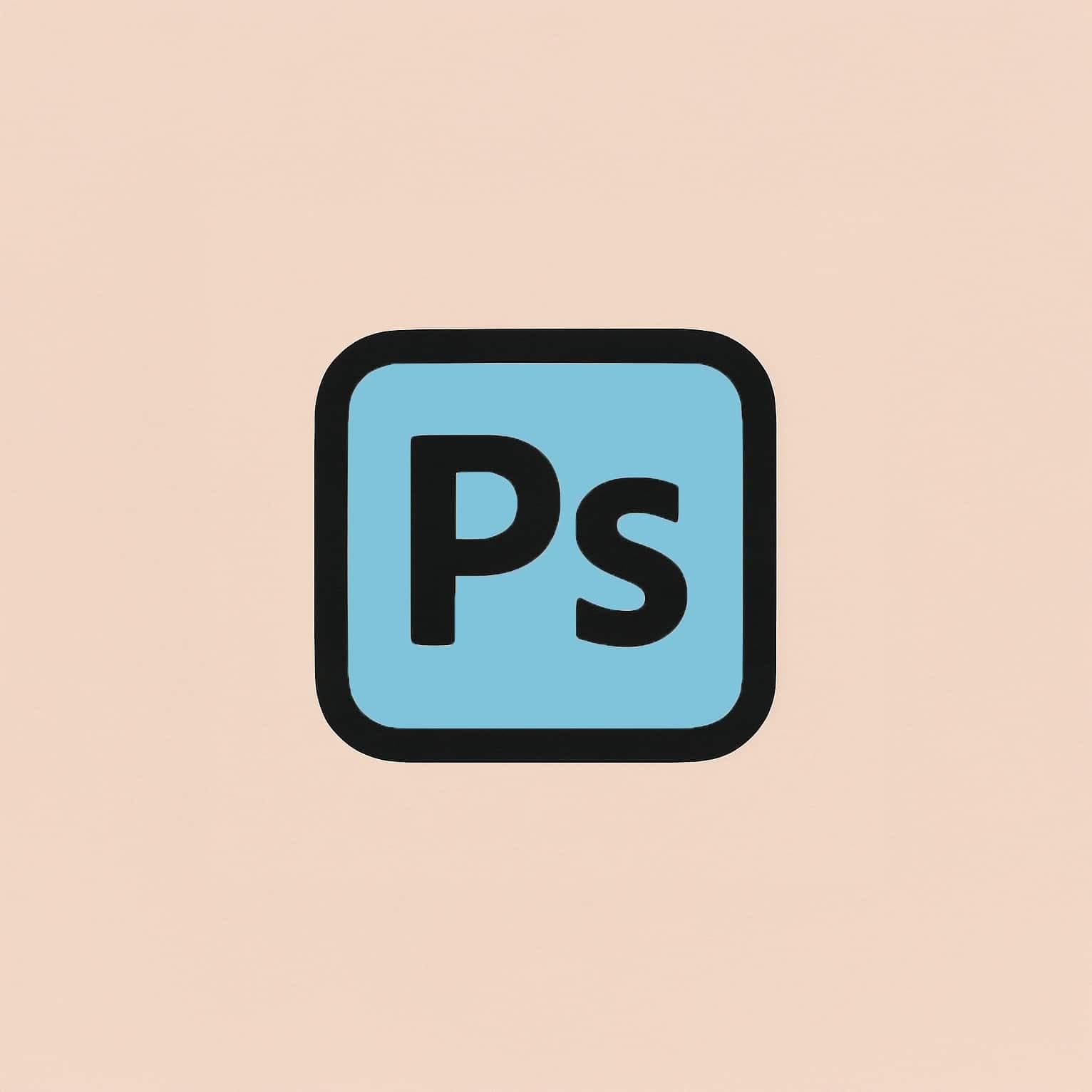
המאמר הבא נלמד איך להוסיף פונטים בעברית לפוטושופ. בכל תוכנה שמשלבת כתיבה בין הכלים השונים שלה, ישנו מאגר מסוים של פונטים. ככה זה בוורד של מיקרוסופט, בפוטושופ של אדובי, ואפילו בצייר הפשוט שמגיע עם מערכת ההפעלה של ווינדוס. אבל, זה לא אומר שזה מספיק לכם כמעצבים.
בעולם בו יש לכם אלפי מתחרים, אתם מחפשים לבלוט, לעשות את הדברים אחרת. ובכל הקשור לגרפיקה – לפעמים הכתב משנה את הכל. פשוט כך.
לכן, רבים מהמעצבים המקצועיים – וגם המשתמשים בפוטושופ – מחפשים כל העת איך להוסיף פונטים בעברית לפוטושופ. פונטים חדשים שיגוונו קצת את עבודתם ואת התוצרים שלהם. כי כשאתה עושה את הדברים בצורה מקורית וחדשנית, ישימו לב אליך ולא לאף אחד אחר.
פוטושופ הוא כלי עיצוב גרפי רב עוצמה, המאפשר לכם ליצור עיצובים מרהיבים. אחד האלמנטים החשובים ביותר בעיצוב גרפי הוא הבחירה בפונט המתאים. פונטים שונים מעבירים מסרים שונים, יוצרים אווירה שונה ומותאמים לסגנונות עיצוב שונים.
אתם כבר ודאי יודעים כי פונט כתב יד יתאים לעיצוב של קטע מיומן אישי למשל, ופונט המחקה כתב רש״י יתאים לעיסוק בטקסט מן המקורות. במאמר זה נלמד איך להוסיף פונטים בעברית לפוטושופ, ונרחיב על אפשרויות שונות לבחירת הפונטים המתאימים.
בנוסף לפוטושופ, תוכנות עיצוב גרפי אחרות מציעות גם הן אפשרות להוסיף פונטים בעברית. פונטים בעברית בקנבה זמינים במגוון רחב, והשימוש בהם הוא אינטואיטיבי וקל. כך גם בתכנות עיצוב נוספות.